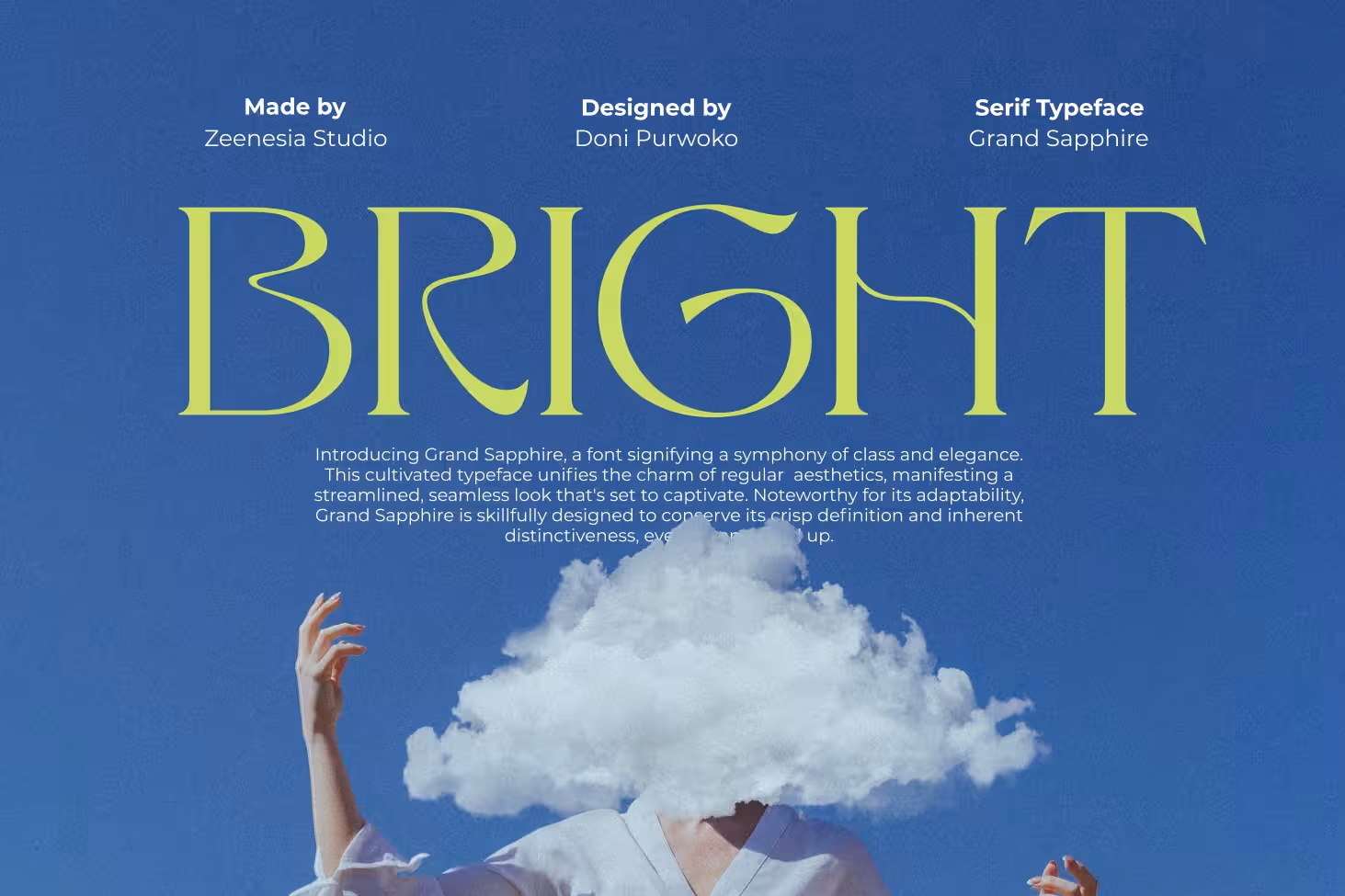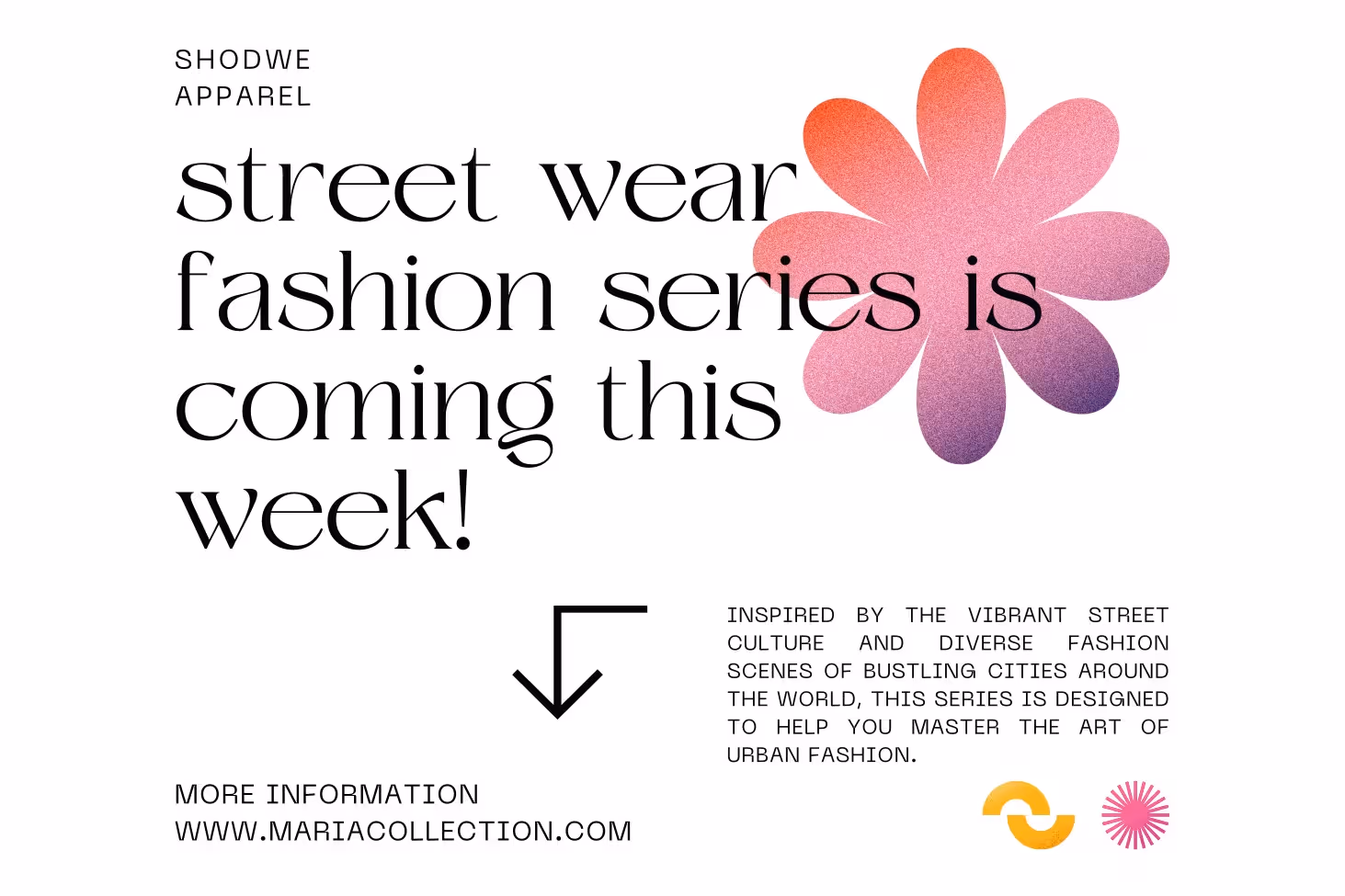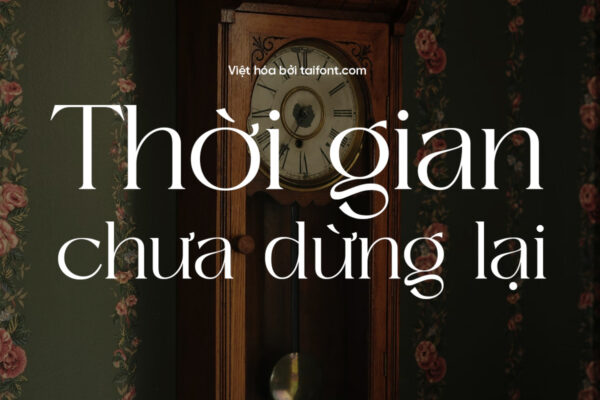
Giới thiệu về Font TF Grand Sapphire Việt hóa
TF Grand Sapphire Việt hóa là một font chữ có chân (serif) nổi bật với thiết kế thanh lịch, tinh tế và đầy cuốn hút. Font này mang đến vẻ đẹp cổ điển kết hợp hiện đại, toát lên phong thái quý phái, đẳng cấp và sự cuốn hút đặc biệt, lý tưởng cho mọi ấn phẩm cần sự tinh xảo và độc đáo.
Với sự tinh xảo trong từng ký tự và tính thẩm mỹ vượt trội, Grand Sapphire là lựa chọn hoàn hảo cho các thiết kế muốn truyền tải sự sang trọng và phong cách, đặc biệt là trong các lĩnh vực:
- Thiết kế bài tạp chí và album ảnh cưới: Hoàn hảo để sử dụng cho các tiêu đề chính, lời dẫn, hoặc nội dung bài viết trong các tạp chí về thời trang, làm đẹp, lối sống cao cấp. Nét chữ có chân của font giúp tăng tính trang trọng và dễ đọc, đồng thời tạo cảm giác cao cấp, thu hút độc giả. Đặc biệt, font rất lý tưởng để viết những câu chuyện, lời dẫn cho từng bức ảnh trong album cưới, giúp album trở nên lãng mạn và ý nghĩa hơn.
- Thiết kế thời trang và làm đẹp: Lý tưởng cho các thương hiệu thời trang, mỹ phẩm cao cấp, từ logo, nhãn mác sản phẩm, đến các lookbook và chiến dịch quảng bá bộ sưu tập. Font này giúp truyền tải vẻ đẹp thanh lịch, đẳng cấp và độc đáo của sản phẩm, nâng tầm giá trị thương hiệu.
- Thiết kế thiệp cưới: Phù hợp để viết tên cô dâu chú rể, lời mời cưới, hoặc các thông tin chi tiết trên thiệp cưới, menu tiệc, bảng tên khách mời. Những nét chữ tinh tế, sang trọng sẽ biến mỗi tấm thiệp thành một tác phẩm nghệ thuật, mang đậm dấu ấn cá nhân và sự lãng mạn, trang trọng cho ngày trọng đại.
Với TF Grand Sapphire Việt hóa, bạn có thể dễ dàng thổi hồn tinh tế, sang trọng và vẻ đẹp hoàn hảo vào các thiết kế, tạo ra những sản phẩm không chỉ đẹp mắt mà còn đầy cảm xúc và sức hút đặc biệt.
Font Việt hóa TF Grand Sapphire